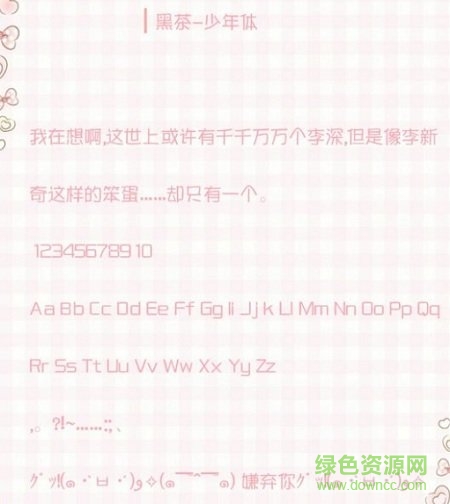
黑茶少年體ttf是一款字跡清雅端正的手寫字體,有著圓潤(rùn)方形外觀,給文字更加飽滿大眾化的閱讀體驗(yàn),很有幼圓體和卡通字體的風(fēng)格,快來(lái)綠色資源網(wǎng)試試吧!
黑茶少年體將時(shí)光裝進(jìn)茶里,將茶裝進(jìn)字里,讓它可以永久的流傳和回味,撲鼻而來(lái)的濃香和懷舊時(shí)光,磨成了這款字體,給你午后初陽(yáng)高照般的溫暖體驗(yàn)。
黑茶少年體是一款比較好看舒適的少年體,更富有青春活力而不造作,有著不粗的藝術(shù)呈現(xiàn)和表達(dá)能力,可以廣泛使用在藝術(shù)設(shè)計(jì)、包裝設(shè)計(jì)等藝術(shù)設(shè)計(jì)場(chǎng)合哦!